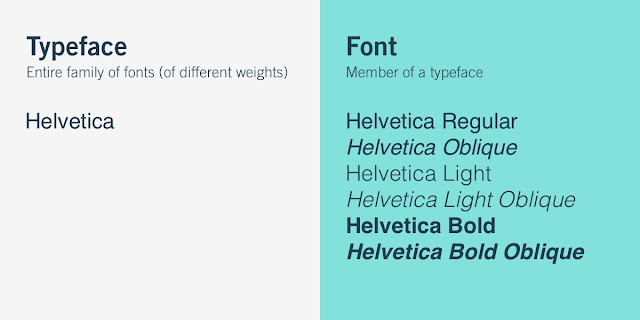
Free and Premium Quality Fonts - Best Premium FontsHelvetica verdana arial century gothic dan calbiri. Pada gilirannya font serif adalah font yang memiliki unsur serif sedangkan sans serif adalah font yang tidak memilikinya karenanya terdapat kata sans. San serif tidak memiliki garis kecil.
Kurva poros yang miring ke kiri 2.
Font sans serif adalah. Dalam definisi yang sangat sederhana serif adalah detail berupa stroke dari sebuah hurufsaya sih menyederhanakannya dengan istilah ekorfont serif adalah font yang memiliki detail berupa ekor dari font tsb. Light thin regular dan book berkat fontfabric type foundry. Istilah sans serif berasal dari bahasa perancis sans yang berarti tanpa dan serif yang dalam bahasa belanda memiliki arti garis. Jenis ini tidak memiliki hiasan atau guratan kecil seperti ujung dari karakter tipografi serif.
Jika serif pada setiap akhir huruf terdapat garis kecil. Font serif lebih dekoratif dan tampak seperti memanjang dari ujungnya sedangkan font sans serif memiliki ujung yang bersih dan dapat dikatakan sangat presisi. Arial futura avant garde bitstream vera sans century gothic dan lain sebagainya. Font san serif ini kebalikan dari font serif.
Lengkungan serif counterstroke. Arial futura avant garde bitstream vera sans century gothic dan lain sebagainya. Kata sans serif berasal dari bahasa prancis sans berarti tanpa dan serif berarti kaithuruf sans serif atau tanpa kait sendiri mulai populer pada awal abad ke 20 dimana pada saat itu sans serif mulai diperkenalkan pada saat ini sans serif banyak digunakan dalam teks digital karena. Berikut adalah contoh font san serif yang lainnya.
Serif dan sans serif. Klasifikasi huruf dibuat dengan landasan latar belakang histori perkembangan tipografi. Popularitasnya meningkat dan beberapa menyebutnya helvetica font gratis ada kuartet tambahan baru pada keluarga ini. 5 jenis font terbaik sans serif yaitu.
Didasarkan pada font gratis bebas neue ryoichi tsunekawa membuat font sans serif ini. Dalam dunia tipografi huruf sans serif adalah suatu huruf yang tidak memiliki kait pada bagian ujung hurufnya. San itu artinya tanpa. Font sans serif adalah tipografi yang terdiri dari guratan garis sederhana.
Contoh font yang digolongkan kepada sans serif adalah. Jenis font slab serif ini adalah salah satu jenis font yang bentuknya memanjang dan sering digunakan pada media surat kabar atau biasa juga digunakan pada buku buku. Jenis huruf sans serif adalah jenis huruf yang tidak memiliki garis garis kecil dan bersifat solid. Pada dasarnya font dapat kita klasifikasikan kedalam dua kategori.
Arial comic sans ms tahoma verdana. Font adalah sesuatu yang penting dalam desain grafis baik desain logo ataupun untuk melakukan penulisan. Berikut adalah contoh font serif yang lainnya. Contoh font yang digolongkan kepada sans serif adalah.
Jenis huruf seperti ini lebih tegas bersifat fungsional dan lebih modern. Ada kontras antara tebal dan tipis garis font. Pengertian font font merupakan sebuah rupa huruf yang mempunya ukuran gaya dan berat tertentu wikipediasalah satu dari klasifikasi font tersebut adalah font jenis serif dan juga font sans serif.